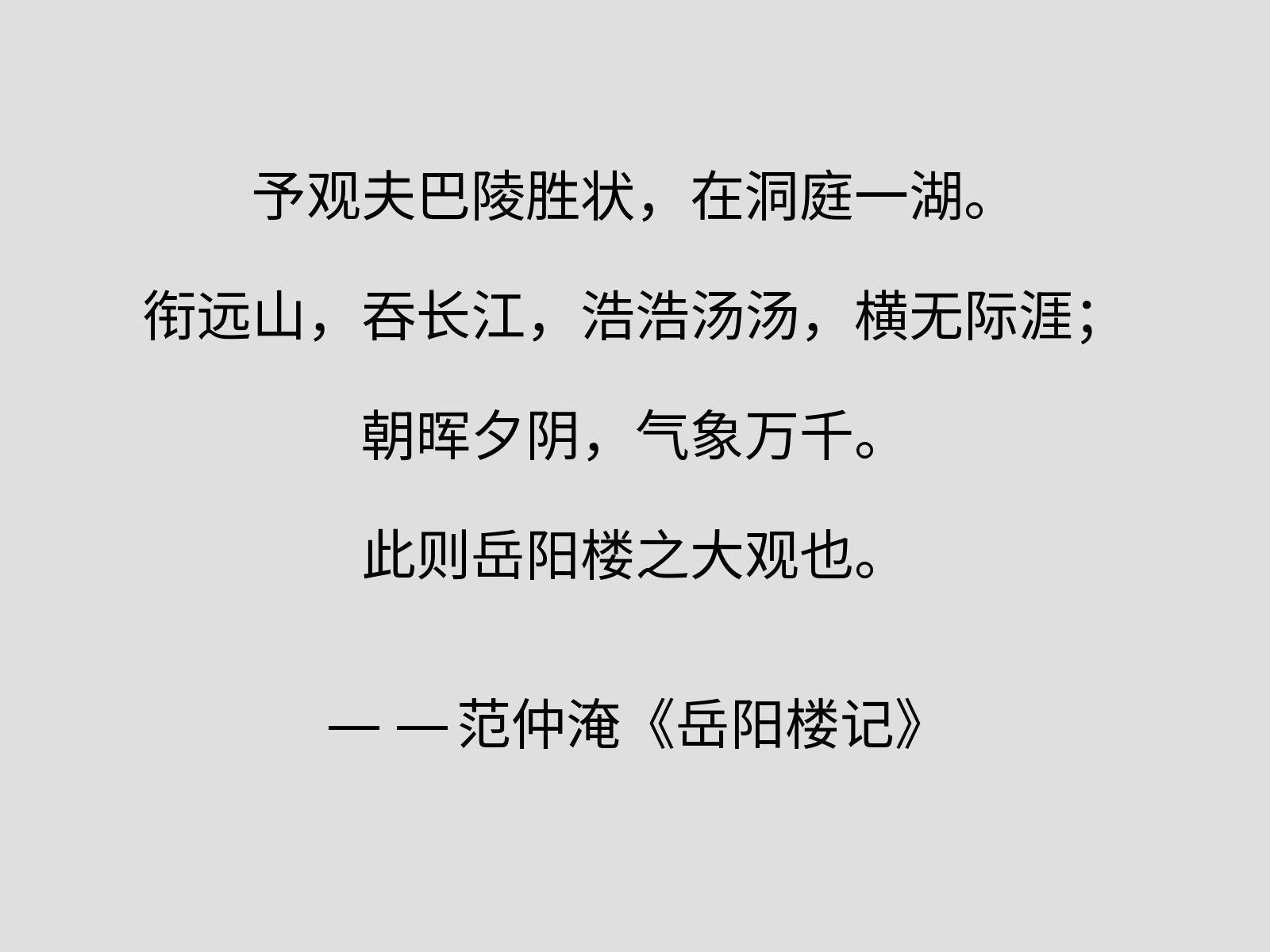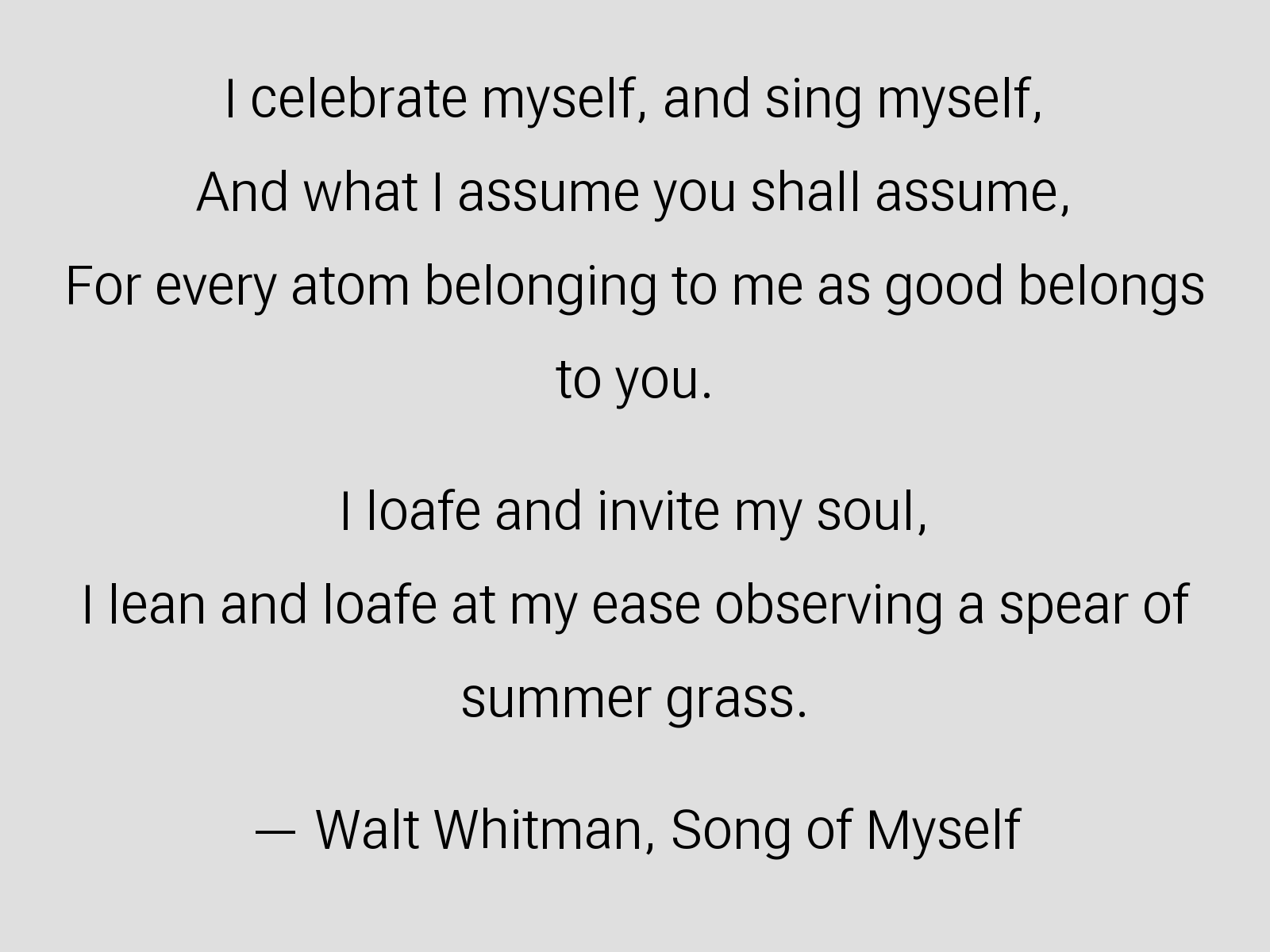
嗷呜等高体这是一款商用免费的字体,它的特别之处在于让汉字和西文(包括大写字母和数字)达到相同的高度。这款字体主要基于《Roboto Flex》和《文渊黑体》这两个开源项目开发而来,设计目的就是为了方便处理那些需要汉字与西文并排且视觉高度一致的场景,比如说食品饮料的包装设计、产品标牌、说明书排版等等,都能让它发挥很好的作用。
• 新增下方线倾斜的 ≤ ≥ 和不伸到降部的 ( ) [ ] { },调用蝌蚪形弯引号 ‘ ’ “ ”。
这些是默认调用的,原版字形可通过 ss01 调取。
• 调整西文。
• 微调窄体下汉字等字符字重。